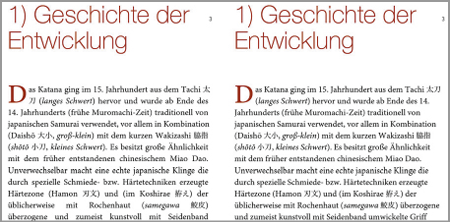
Satzart
In Romanen ist es gang und gäbe, den Lesetext im Blocksatz zu setzen. Beim ePub-Format haben wir allerdings das Problem, dass die meisten E-Reader momentan keine Silbentrennung kennen. CSS bietet keine Kontrolle über Trennungen. Es gibt zwar JavaScript-Bibliotheken, die mit Trennungen umgehen können, und auch die neue CSS3-Eigenschaft text-justify, aber dies steckt noch in den Kinderschuhen. Auf jeden Fall hat man keine richtige Kontrolle darüber, wie und wo getrennt wird. Es ist ein typisches Merkmal von E-Books, dass sie sich der Breite des Anzeigegerätes anpassen, so wie sich Zeilen im Browser anpassen, wenn das Fenster verkleinert wird. Der Umbruch kann sich ebenfalls ändern, wenn Nutzer sich dazu entschließen, die Schrift größer einzustellen. Dieses Feature haben E-Reader heutzutage in der Regel integriert und liefert auch ein gutes Argument für E-Books. Man kann im ePub zwar auch sogenannte Soft Hyphens benutzen und auf diese Weise Trennvorschläge einbauen (»bedingter Trennstrich« in InDesign). Bei richtig langen Wörtern mag dies sinnvoll sein, aber die Volltextsuchfunktionen der E-Reader können nicht unbedingt damit umgehen und sie werden auch nicht von allen angezeigt. Solange es für die Silbentrennung keine gute, standardisierte Lösung gibt, empfehlen wir, E-Books besser linksbündig zu setzen.
Abbildung: Im ePub wird nicht getrennt, daher erhält man im Blocksatz viele hässliche Löcher.
Deshalb besser linksbündig setzen.